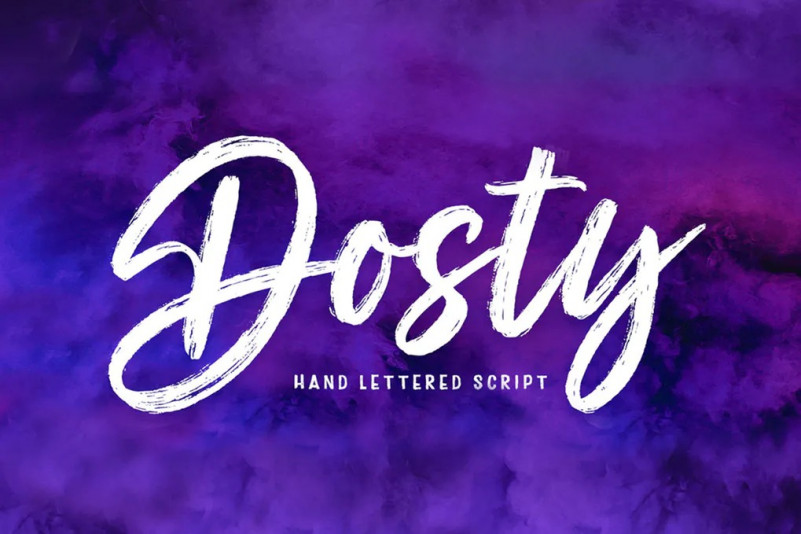
Dosty Font
Dosty est une police de pinceau texturé unique, parce que cette police de pinceau est faite numériquement. approche contemporaine de la conception, et a souligné et a également plusieurs ligatures.
Convient pour une utilisation dans les dessins de titres tels que les livres de titres, les dessins de papeterie, les citations, l’image de marque, les Logos, les vêtements, les invitations, les cartes de vœux, les t-shirts, les dessins d’emballages, les affiches et plus encore.